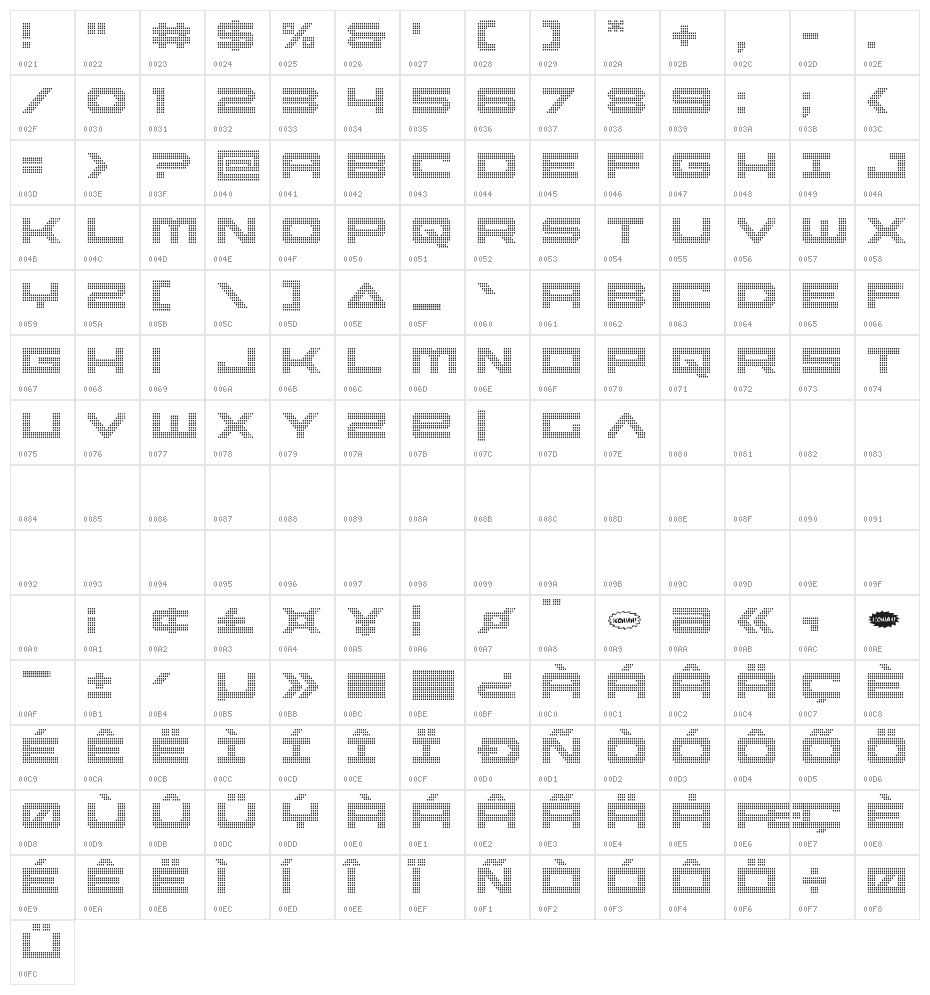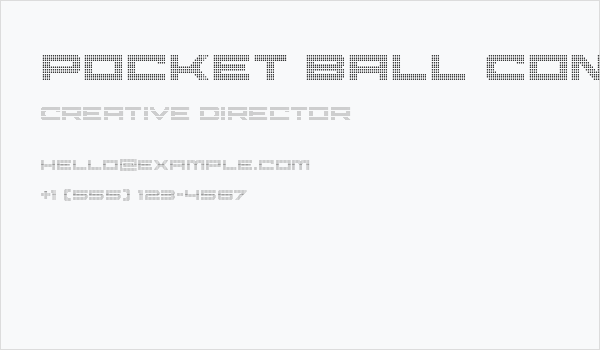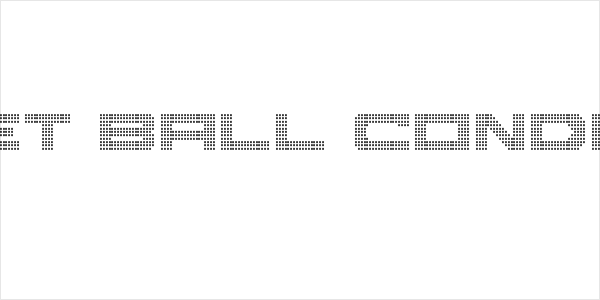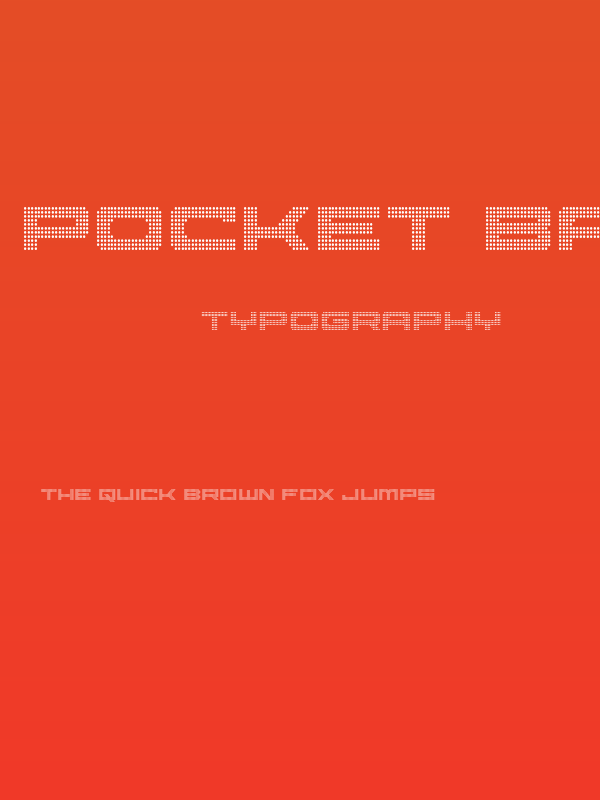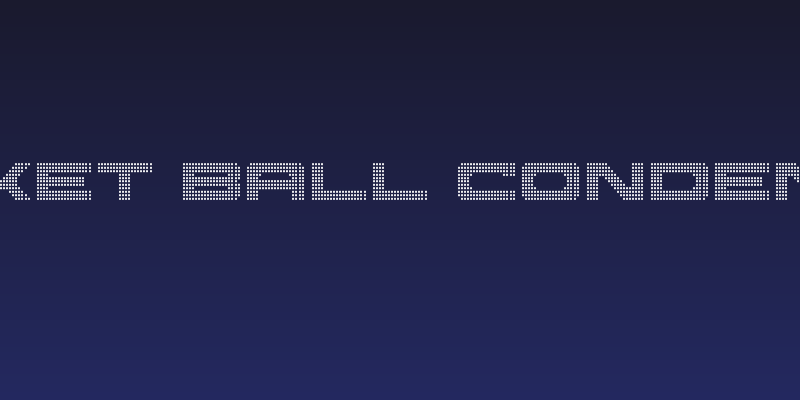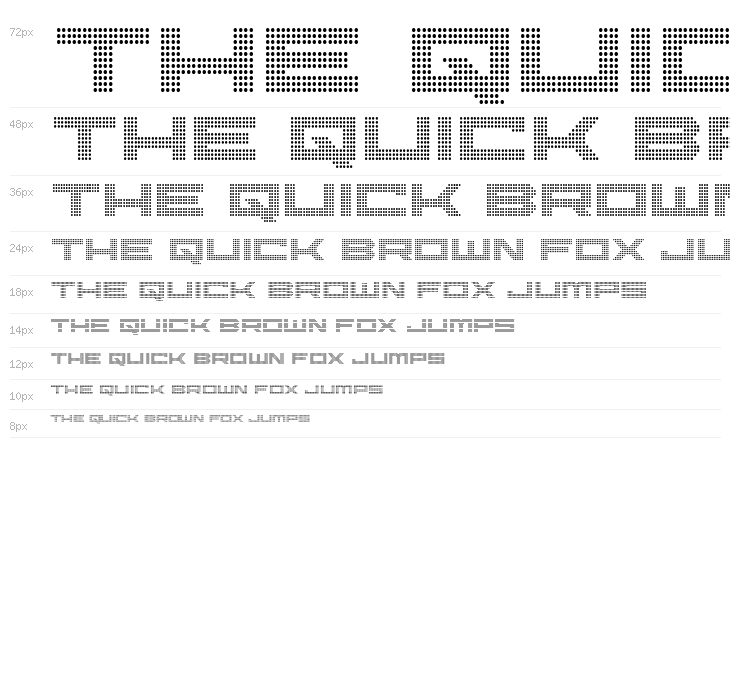
Pocket Ball Condensed Font
| Caso d'uso | Headlines, Logos, Digital displays |
| Progetti proposti | Ideal for tech-themed projects, digital displays, futuristic branding, or any design needing a modern, tech-inspired look. |